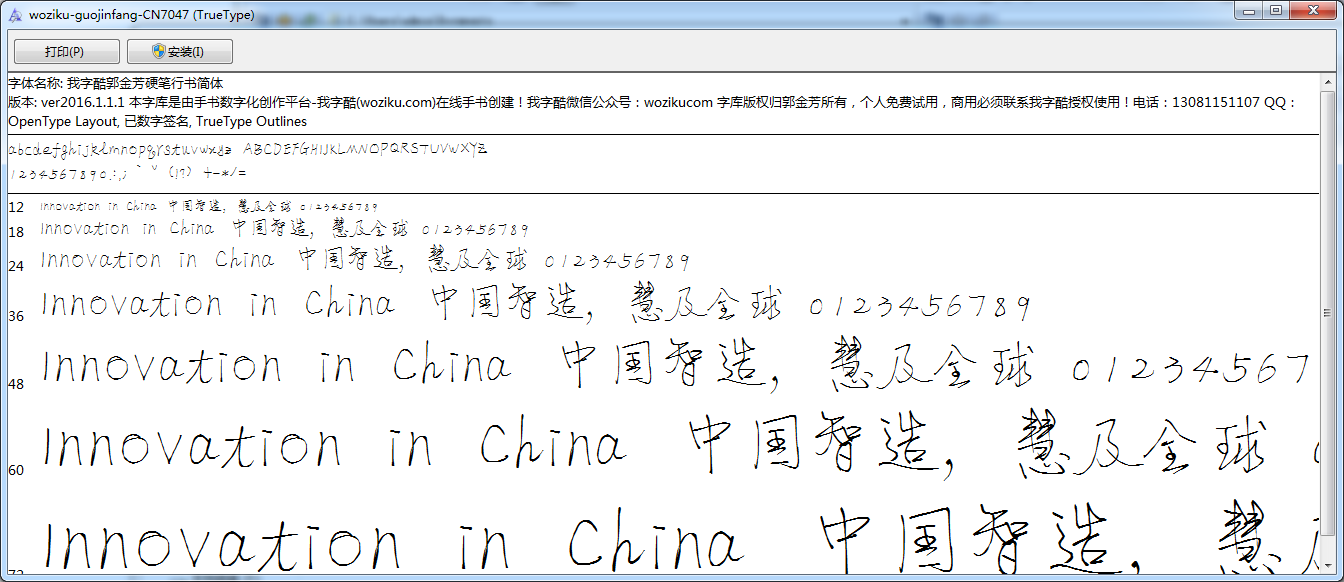
郭金芳硬筆行書(shū)字體是一款比較好的行書(shū)字體,特別適合用于行書(shū)設(shè)計(jì)、廣告設(shè)計(jì)、海報(bào)設(shè)計(jì)等,方便快捷,有需要者歡迎到綠色資源網(wǎng)下載!
字體外似柔潤(rùn)而內(nèi)實(shí)堅(jiān)強(qiáng),形體端秀而骨架勁挺,整體字體筆畫(huà)流暢,識(shí)別性強(qiáng),整體風(fēng)格出色